三极真喵空心简体:这款字体运用空心设计体现出立体感,。用儿童写字的简拙,笔画轻松、简洁,童趣随性。风格特征明显,便于寻找图片的字体。字形饱满圆润,轮廓略显臃肥,整体明快可爱。适用于少儿类读物、书刊、品牌广告、包装设计以及社交网络个性化用字。
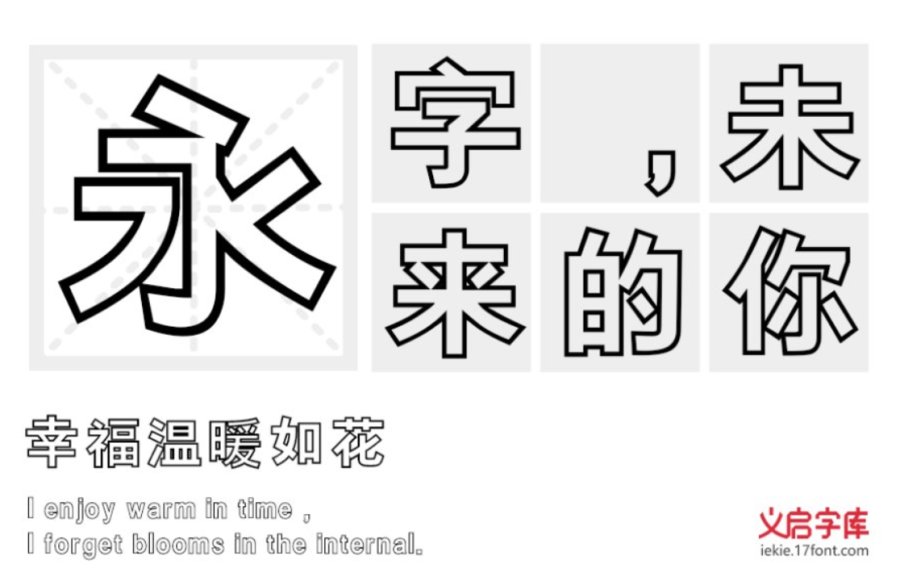
义启白加黑体:这款字体加深了黑色线条与留白空间展现了视觉的冲击力。字形整体结构呈现正字形,浑厚有力、端庄大方。适用于广告设计、logo设计、招牌设计等设计领域。
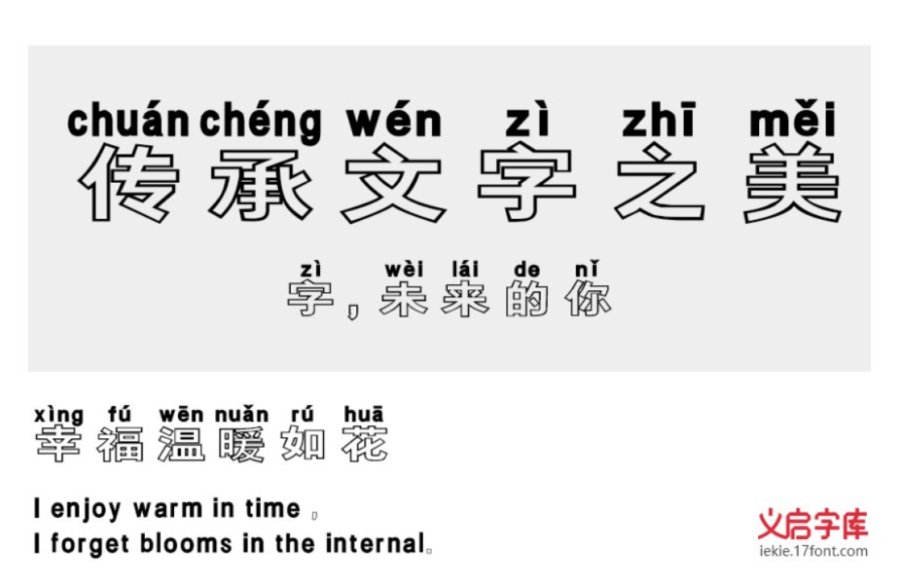
做个俗人黑白分明:这是一款拼音空心体,设计师有意识地把字的部分笔画进行夸大、缩小,或者移动位置,改变字的重心,使构图更加紧凑,字形更别致,具有新颖醒目的效果。适用于产品包装、海报和书刊设计、影视综艺等领域。平常我们见到的字体大多都是实心的纯色字体,觉得设计过于单调。空心字体是一种视觉化设计,拜托了基本字体的束缚、增加大量的留白使得字体更加立体赋予感染力。让字体看起来更有韵味提升逼格,并且艺术感十足。